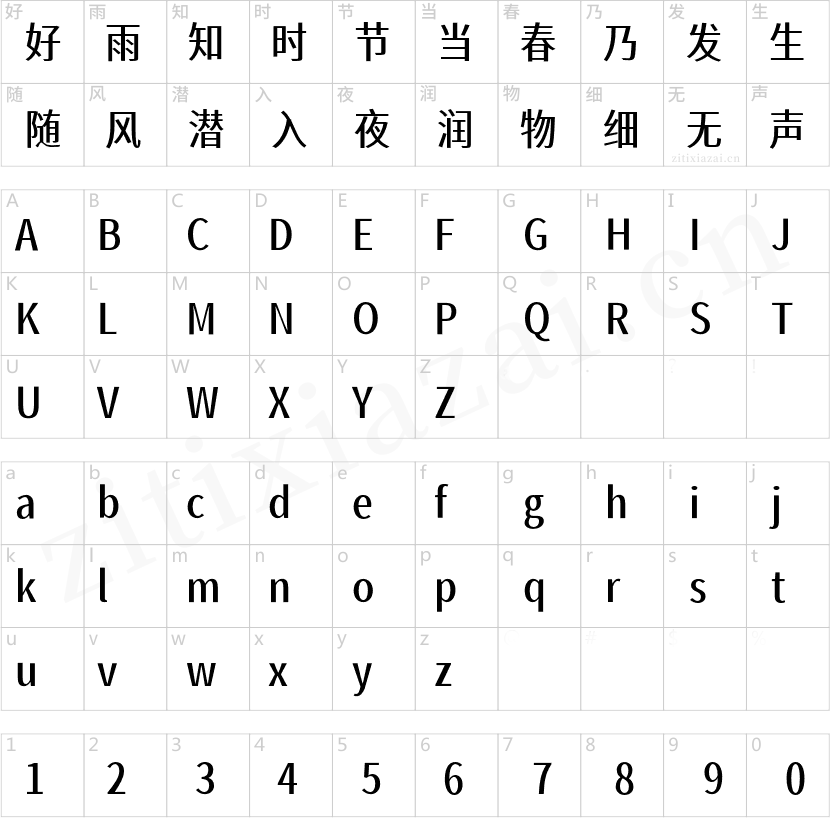
寒蝉有机体
寒蝉有机体,这款字体结构工整、笔画清晰,兼顾美观与易读性,适用于标题、正文、海报、包装、LOGO 等多种场景。字形优雅稳定,风格百搭耐看,适配日常排版与创意设计,让文字呈现更舒适、更具质感。寒蝉有机体一笔一画,皆是细节,以均衡的比例、流畅的线条打造舒适视觉体验,字形端正大气,风格简约现代。无论是商业设计、品牌宣传还是日常排版,都能轻松驾驭,让文字更有格调与力量。寒蝉有机体字体下载。
• 字体说明:寒蝉有机体是基于思源黑体进行逆反差美术风格字体探索,尝鲜版。